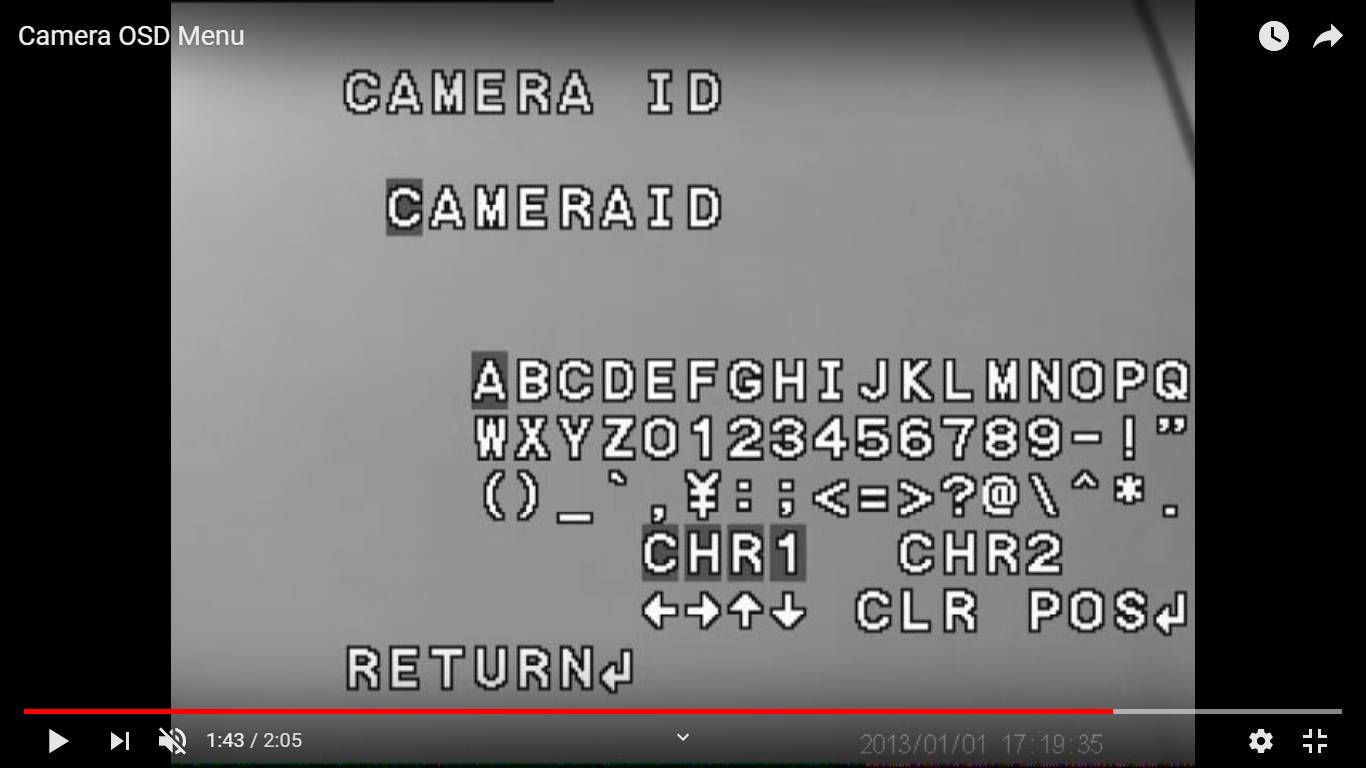
VHS font
Prosímvás, poradíte mi, jak se jmenuje tenhle font?
Vím, že byl využíván na video záznamech...
Na obrázku máte příklad.
VHS font
Tento font se jmenuje VCR OSD Mono..hezký den! :)
Otevři si mapu znaků a porovnávej. Chvíli to možná potrvá.
To jsem zkoušel, ale žádný font neodpovídá znakům :D